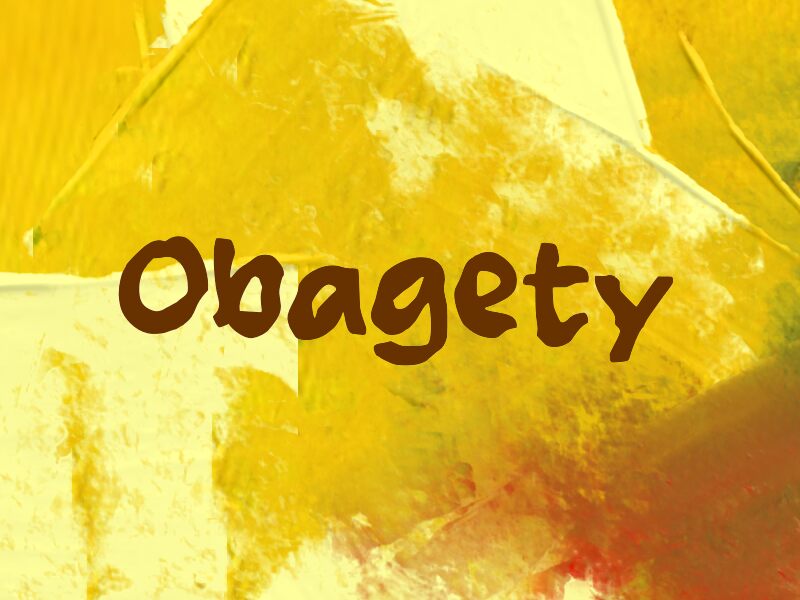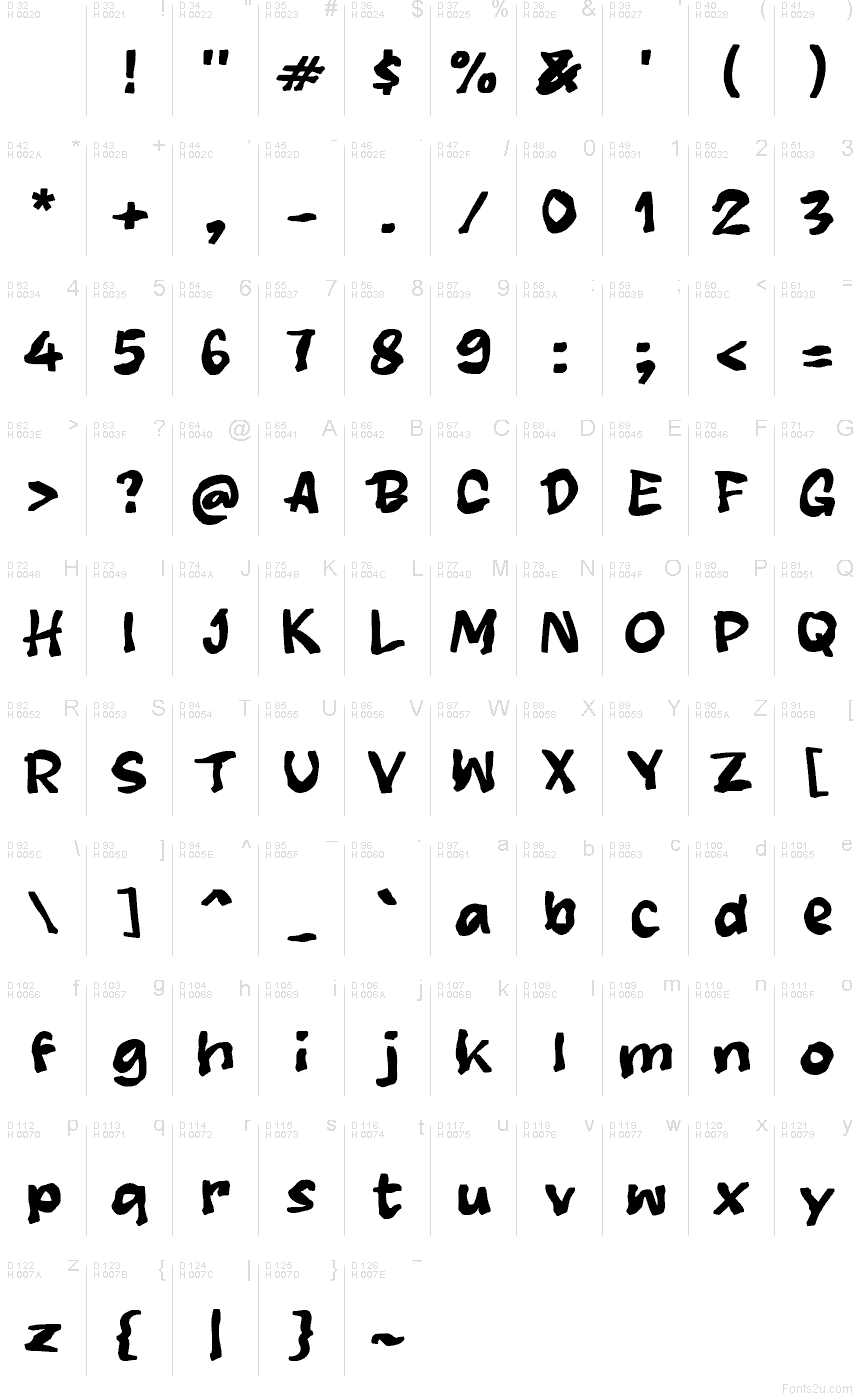
Obagety
Obagety de Wep es una tipografía tipo brush gratuita, definida por formas anchas y cargadas de tinta que parecen más estampadas o pintadas que dibujadas con precisión. Esta silueta robusta le da a las letras un rebote artesanal y contundente, con aperturas redondeadas y bordes irregulares que mantienen una textura viva en todo el set.
Es ideal para titulares cortos, carteles, portadas de álbumes, diseño de packaging y gráficos para redes sociales, especialmente cuando el diseño pide una masa pintada más ruda en lugar de un trazado impecable. Su volumen de bordes suaves aporta a logotipos y rótulos una presencia orgánica y cercana, que se siente inmediata y casual en lugar de demasiado pulida.